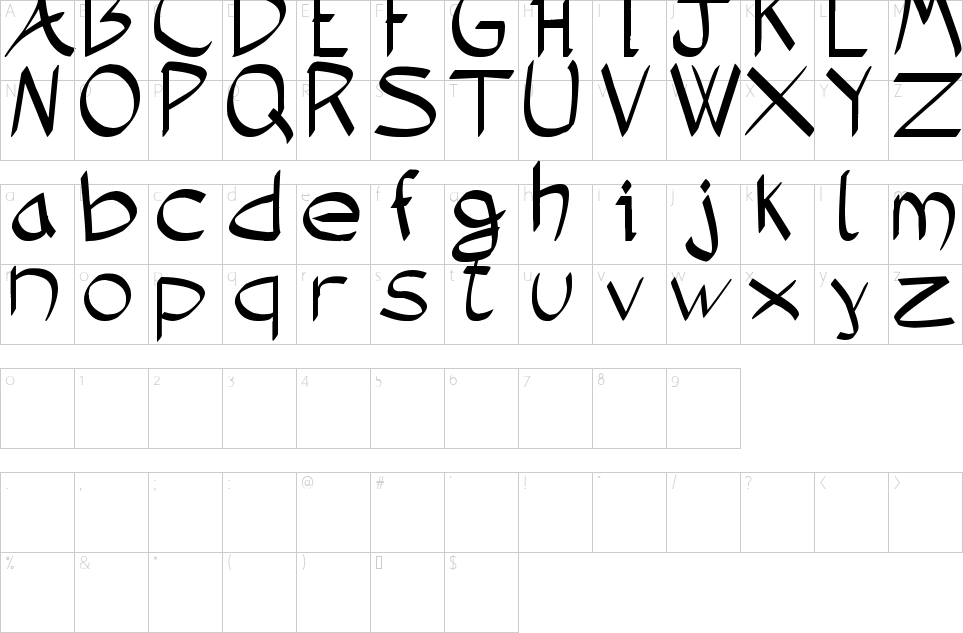
A Demoniatibu Font é uma elegante seleção para adicionar um toque único a seus projetos digitais. Desenhada por Southype, esta tipografia destaca-se não apenas pela sua facilidade de uso mas também pela sua rica aparência que combina elementos modernos com arco-íris e expressões emotivas, criando uma atmosfera envolvente e natural perfeita para aplicações como redes sociais, blogs pessoais ou qualquer projeto de design gráfico. A Font Demoniatibu tem sido adquirida 2400 vezes, demonstrando sua popularidade entre designers independentes que buscam novas opções para seu trabalho. Com um design cuidadosamente elaborado, a Demoniatibu é uma ótima escolha para quem procura algo mais do que apenas uma fonte clássica. Seja você um designer ou amante de arte digital, essa fonte oferece uma maneira interessante e versátil de expressar sua criatividade.